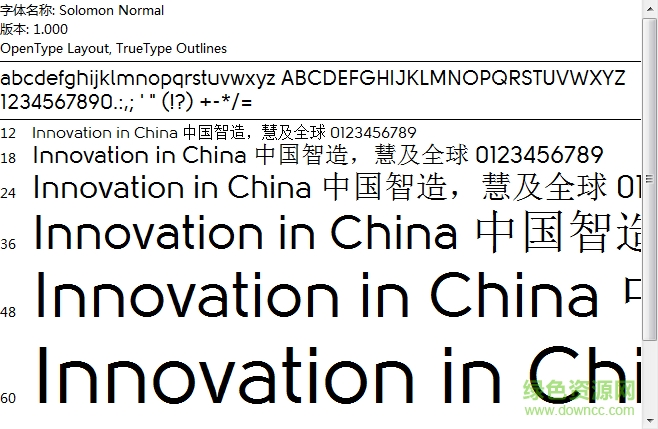
solomon bold字體
solomonbold是solomon字體的黑體,字體大方明亮,中文采用黑體楷書、英文書寫圓潤有型,很有藝術(shù)字體之美,喜歡的朋友就來綠色資源網(wǎng)體驗(yàn)吧!
solomon字體介紹
solomon字體包括solomon bold和solomon normal,中文書寫無特別亮點(diǎn),英文書寫大氣莊重,又不失活潑可愛,是一款使用廣泛的英文字體,可運(yùn)用于廣告設(shè)計(jì)、藝術(shù)設(shè)計(jì)、海報(bào)設(shè)計(jì)等諸多場合。